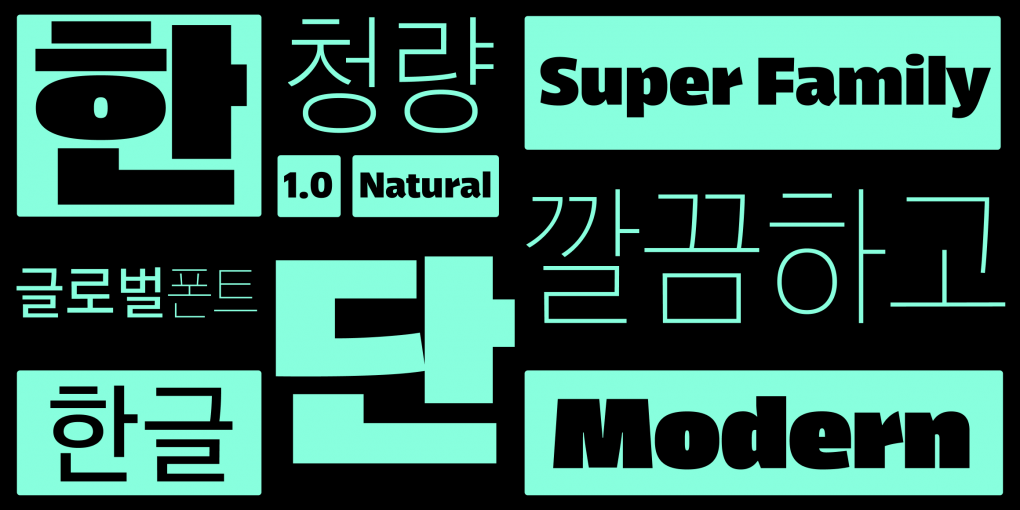
지난 7월 17일, 산돌구름에 반가운 소식이 있었어요! 이미 국내에서 두터운 팬층을 보유하고 있는 함민주 브랜드사의 입점 소식입니다. 이미 소식을 들은 분들의 뜨거운 환호가 가득한데요, 이 기세를 몰아, 구독자 여러분들에게만 공개하는 함민주 디자이너와의 일문일답을 공개합니다.
반갑습니다! 함민주 브랜드에 대한 전반적인 소개를 부탁드려요.
안녕하세요 독일 베를린을 기반으로 활동하는 타입디자이너 함민주입니다. 한글의 다양한 표정을 연구하며 그려요. 대표작으로는 둥켈산스, 블레이즈페이스 한글이 있습니다. 최근에는 마르크 프룀베르크와 함께 한글과 라틴, 두 문화권을 글자체로 연결하려는 미션을 갖고 하이퍼 타입 파운드리를 시작했어요.
타입디자인의 매력에 빠진 계기가 있으신가요?
대학교 1학년 수업에 한글 디자인 수업이 있어서 자연스럽게 비교적 일찍 글자체 디자인을 접했어요. 제가 만든 글자로 디자인 작업에 활용하는 게 재미있고 신기한 경험이었어요. 졸업 전시 도록에도 제가 만든 폰트를 사용했고요. 그때부터 꾸준히 다양한 한글의 모습을 탐구했고, 졸업 후 실무에서 일하면서 라틴 폰트에 대한 지식과 경험이 부족하단 걸 느껴 유학을 결심했죠. 모든 한글 폰트에는 라틴 문자가 포함되어 있으므로 더 완성도 높은 폰트를 만들기 위해, 한글과 잘 어울리는 라틴을 그리기 위해 더 배우고 싶었어요.
국내외 기업들과 다국어 프로젝트를 주로 진행하셨는데요, 다국어 프로젝트에 대한 노하우가 있다면 알려주세요!
다국어 프로젝트는 각 문자 디자이너가 그 느낌을 얼마나 잘 공유하느냐가 중요한 것 같아요. 문화적 배경과 디자인 문법이 다른 두 문자가 잘 어울려야 하기 때문이죠. 외국 디자이너들과 협업할 때 라틴 디자인에는 베이스라인, 엑스 하이트 등 기준선이 뚜렷하게 정해져 있는데, 한글 디자인에 기준선이 없는 것을 의아해하더라고요. 협업할 때 한글 문자의 구조, 시각적인 무게 중심, 회색도 등을 이해시키는 게 중요한 것 같아요.
산돌구름에 입점하는 폰트 중 특별하게 추천하고 싶은 폰트가 있으신가요?
뉴트로닉한글이요. 고딕 (민부리) 스타일로 깔끔하고 청량감 있는 글자체입니다. 라틴은 마르크가 그렸고, 기존의 고딕(민부리)을 재해석해서 그에 어울리는 한글을 그렸어요. Thin부터 Heavy까지 굵기가 다양해서 디자인에 사용하시기 편할 거에요. 특히 가장 굵은 Heavy는 강한 존재감을 자랑합니다. 포스터나 책 제목용으로 사용하시면 눈에 확 띄어요. 또한 가장 가는 Thin굵기는 밝은색으로 어두운 배경에 사용해 보시는 것을 추천합니다.